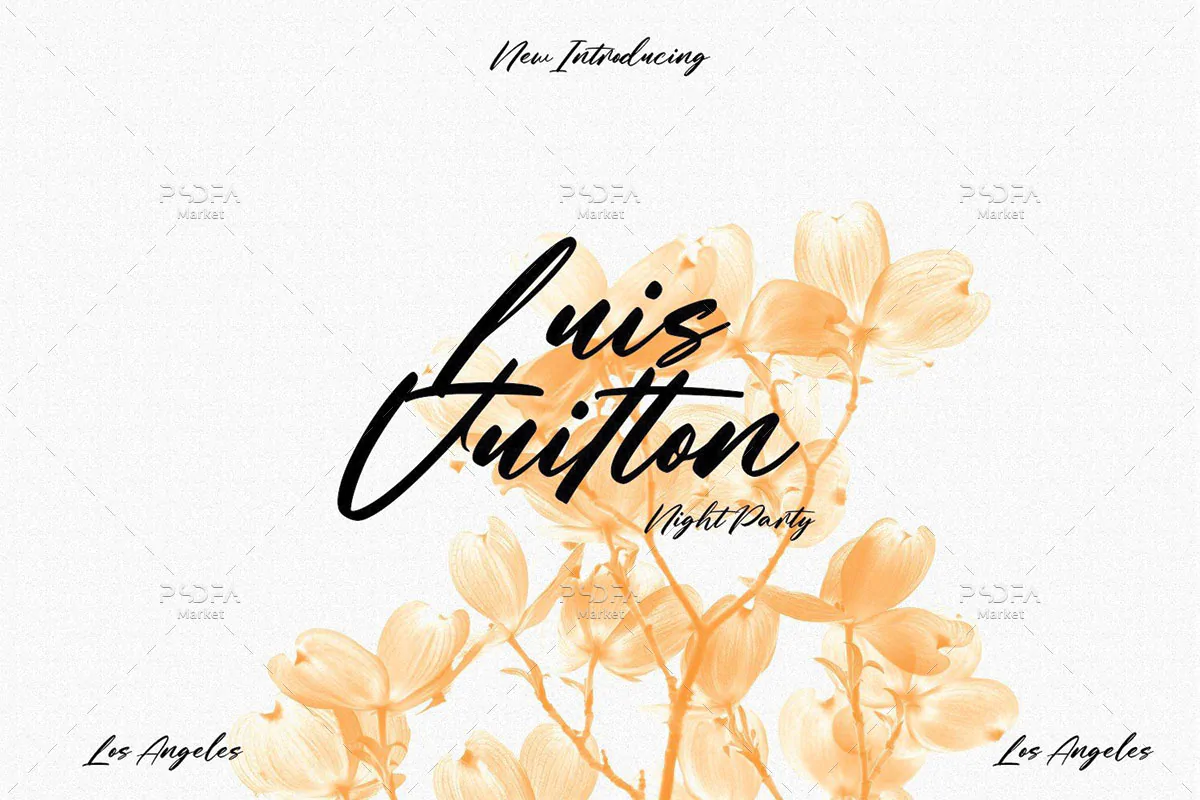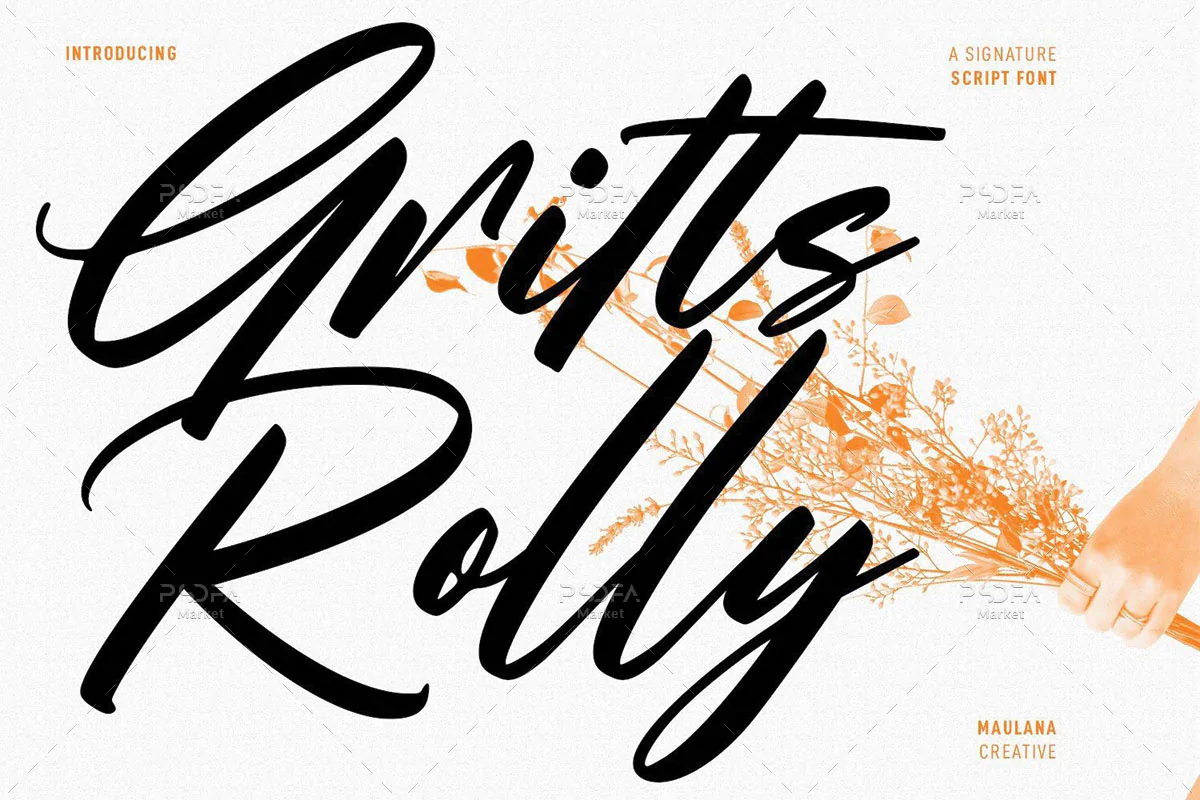
فونت خوشنویسی سرهم Gritts Rolly
فونت خوشنویسی سرهم
فونت خوشنویسی سرهم Gritts Rolly یک قلم دستنویس انگلیسی است که مناسب جهت استفاده در طرح و پروژههای گرافیکی مختلف میباشد. فونت Gritts Rolly با وزن معمولی طراحی شده است که میتوانید از آن در طراحی انواع کارت عروسی، کارت تبریک، طرحهای رمانتیک و عاشقانه ولنتاین، بسته بندی محصولات، آرایشی و بهداشتی، لوازم التحریر و … استفاده کنید.